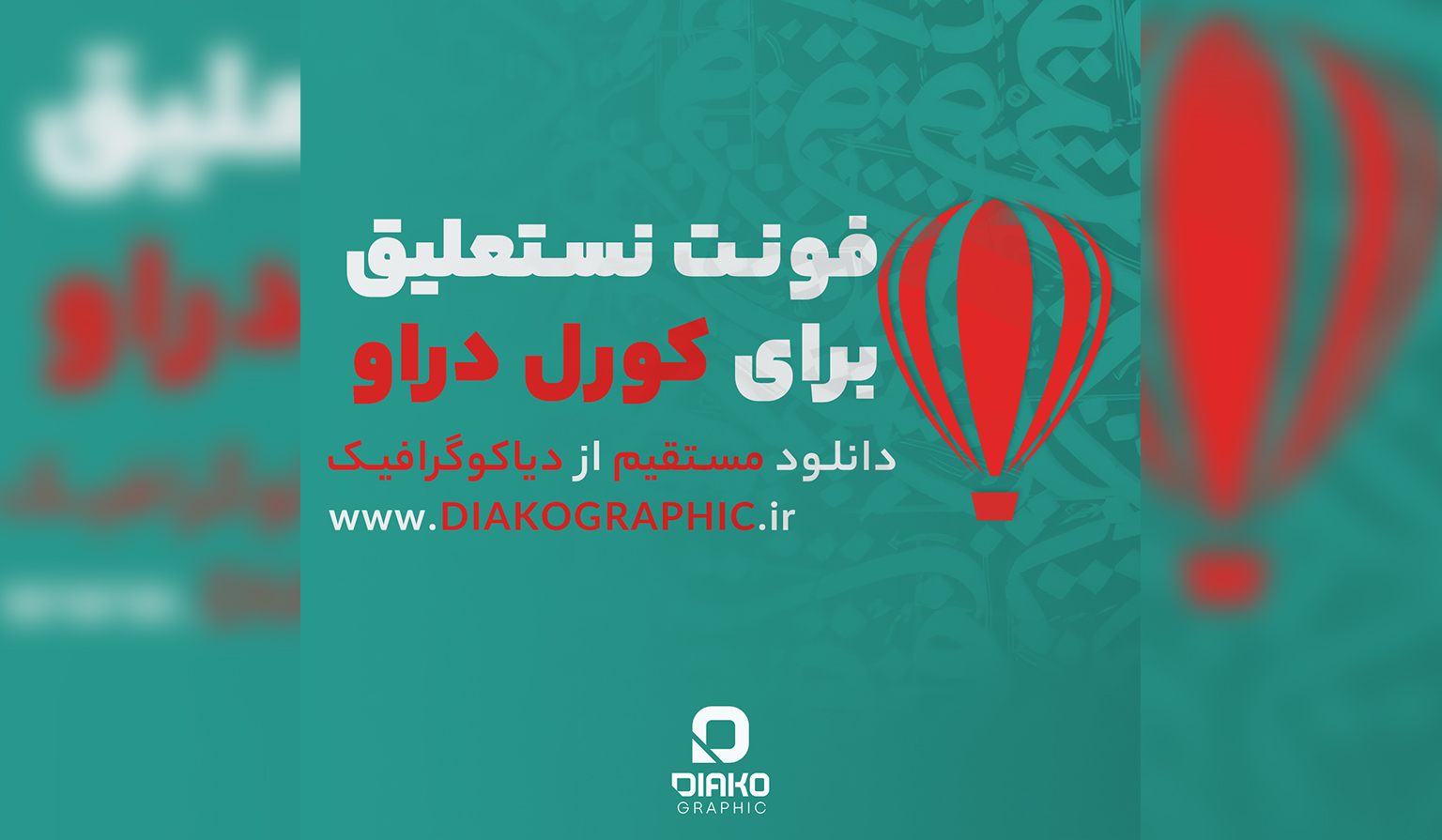
آیا فونت نستعلیق برای کورل دراو وجود دارد؟
در دنیایی که گرافیک دیجیتال و نرمافزارهای طراحی همهچیز را به سمت سادهگرایی و خطوط مدرن سوق دادهاند، هنوز هم هیچ فونتی نتوانسته جای زیبایی و روح نستعلیق را بگیرد. فونت نستعلیق نه فقط یک قلم، بلکه یادآور قرنها فرهنگ، هنر، شعر و ادبیات ایرانی است. حالا تصور کنید این زیبایی خیرهکننده را بتوانید به طراحیهای گرافیکی خود در نرمافزار قدرتمند کورل دراو (CorelDRAW) اضافه کنید!
اما این کار بهسادگی نصب یک فونت نیست. برای استفاده از فونت نستعلیق برای کورل دراو باید نکاتی را بدانید: چه فونتی را نصب کنید؟ چطور آن را در کورل بهدرستی نمایش دهید؟ چرا برخی فونتها دچار شکستگی میشوند؟ در این مقاله جامع از دیاکوگرافیک، پاسخ همهی این پرسشها را با زبانی ساده اما حرفهای برای شما شرح دادهایم.
چرا فونت نستعلیق برای کورل دراو اهمیت دارد؟
بسیاری از طراحان تازهکار هنگام اجرای فونت نستعلیق در کورل دراو با مشکل مواجه میشوند. دلیل این مشکل، ناسازگاری برخی فونتهای فارسی با ساختار موتور تایپ کورل است. این مشکلات شامل جدا شدن حروف، جابجایی کلمات، یا حتی عدم شناسایی فونت در محیط نرمافزار است.
اما چرا طراحان اصرار دارند از فونت نستعلیق در کورل استفاده کنند؟ چون این نرمافزار، قدرت بالایی در طراحی برداری دارد و برای خلق پوسترها، تابلوهای مذهبی، بنرهای مناسبتی، جلد کتاب، بستهبندی محصولات فرهنگی و طرحهای هنری ایرانی، بهترین انتخاب است. وقتی فونت نستعلیق با ظرافتها و انحناهایش در کنار ابزارهای برداری کورل قرار میگیرد، نتیجه چیزی جز یک اثر هنری حرفهای نخواهد بود.
فونت نستعلیق چیست و چه ویژگیهایی دارد؟
فونت نستعلیق برگرفته از خط نستعلیق سنتی ایرانی است. این خط از ترکیب خط تعلیق و نسخ پدید آمده و از قرن هشتم هجری به بعد، به یکی از رایجترین خطوط فارسی در نوشتارهای رسمی، ادبی و دینی تبدیل شد.
ویژگیهای این فونت:
- انحنای زیاد در حروف
- اتصال طبیعی میان حروف
- خطی شناور و روان
- فضای بصری لطیف و متعادل
- تاکید بر زیبایی و فرم بیش از خوانایی سریع
در طراحیهای فرهنگی، مذهبی، سنتی و حتی مدرن که نیاز به هویت ایرانی دارند، استفاده از فونت نستعلیق در کورل دراو میتواند حس اعتماد، احترام و اصالت را در ذهن مخاطب ایجاد کند.
ویژگیهای فونت نستعلیق مناسب برای CorelDRAW
همهی فونتهای نستعلیق برای کورل مناسب نیستند. یک فونت حرفهای برای این نرمافزار باید ویژگیهای زیر را داشته باشد:
۱. فرمت استاندارد (TTF یا OTF)
نرمافزار کورل دراو بهصورت کامل از فرمتهای TTF (TrueType Font) و OTF (OpenType Font) پشتیبانی میکند. فونتهای قدیمی با فرمتهای غیراستاندارد ممکن است در کورل دچار بهمریختگی شوند.
۲. سازگاری با موتور فارسینویسی ویندوز
فونتی که برای تایپ فارسی بهینهسازی نشده باشد، حتی اگر در ورد بهدرستی نمایش داده شود، در کورل ممکن است حروفش از هم جدا شوند. فونتهای حرفهای فارسی، این موضوع را حل کردهاند.
۳. کرنینگ استاندارد و اتصالات صحیح حروف
فاصلهگذاری حرفهای بین حروف باعث میشود نوشتههای شما شکسته و غیرحرفهای بهنظر نرسد. فونت نستعلیق خوب، این اتصال را طبیعی و روان ارائه میدهد.
۴. پشتیبانی از علائم نگارشی و اعراب
برای تایپ متون مذهبی یا اشعار ادبی، فونت باید از تمام علائم نگارشی فارسی و اعراب پشتیبانی کند.
بهترین فونتهای نستعلیق برای کورل دراو
در ادامه، بهترین فونت نستعلیق برای کورل دراو را معرفی میکنیم:
1. فونت ایران نستعلیق (IranNastaliq)
مشهورترین و پرکاربردترین فونت نستعلیق در فضای وب فارسی. این فونت بهصورت TTF ارائه شده و بهخوبی در کورل اجرا میشود.
ویژگیها:
- رایگان و سبک
- بدون بهمریختگی در کورل
- قابل استفاده در پوستر، بنر، تابلو و…
2. فونت شکسته نستعلیق
اگر بهدنبال سبکی متفاوت، هنریتر و خاصتر هستید، نسخههای شکسته نستعلیق انتخاب خوبی هستند. این فونتها در طراحیهای خلاقانه برای جلد مجله، پوستر شعر، یا پروژههای هنری کاربرد زیادی دارند.
نکات مهم در استفاده از فونت نستعلیق در کورل
تبدیل به Curve: قبل از ارسال فایل برای چاپ، متن را به Curve (Ctrl+Q) تبدیل کنید تا فونت دچار بهمریختگی نشود.- تنظیم فاصله حروف: از ابزار Shape در کورل برای تنظیم دقیق کرنینگ حروف استفاده کنید.
- حفظ نسخه فونت: حتماً فایل فونت را کنار فایل کورل نگهدارید تا در دیگر سیستمها نیز بهدرستی اجرا شود.
موارد استفاده از فونت نستعلیق در طراحی با کورل
- طراحی تابلوهای مذهبی (یاحسین، السلام علیک، و…)
- بنرهای تسلیت و ایام خاص
- جلد کتاب و مجلات ادبی
- طراحی کارت دعوت سنتی
- طراحی لوگوتایپ فارسی
- استفاده در بستهبندی محصولات فرهنگی
- طراحی صفحات قرآن، دعا یا متون کلاسیک
نرمافزار کورل دراو با امکانات برداری قدرتمند خود، بستر مناسبی برای خلق آثار بصری حرفهای است. اما چیزی که آثار شما را از دیگران متمایز میکند، انتخاب فونت مناسب است. فونت نستعلیق برای کورل دراو دقیقاً همان ابزاری است که اصالت، زیبایی و هویت ایرانی را به طرحهای شما میآورد.
آیا نستعلیق برای طراحی لوگو مناسب است؟
پاسخ: کاملاً. نستعلیق میتواند هویت برندهایی با اصالت ایرانی یا مذهبی را بهخوبی نمایان کند.
اگر فونت نستعلیق در کورل دچار شکستگی شد چهکار کنم؟